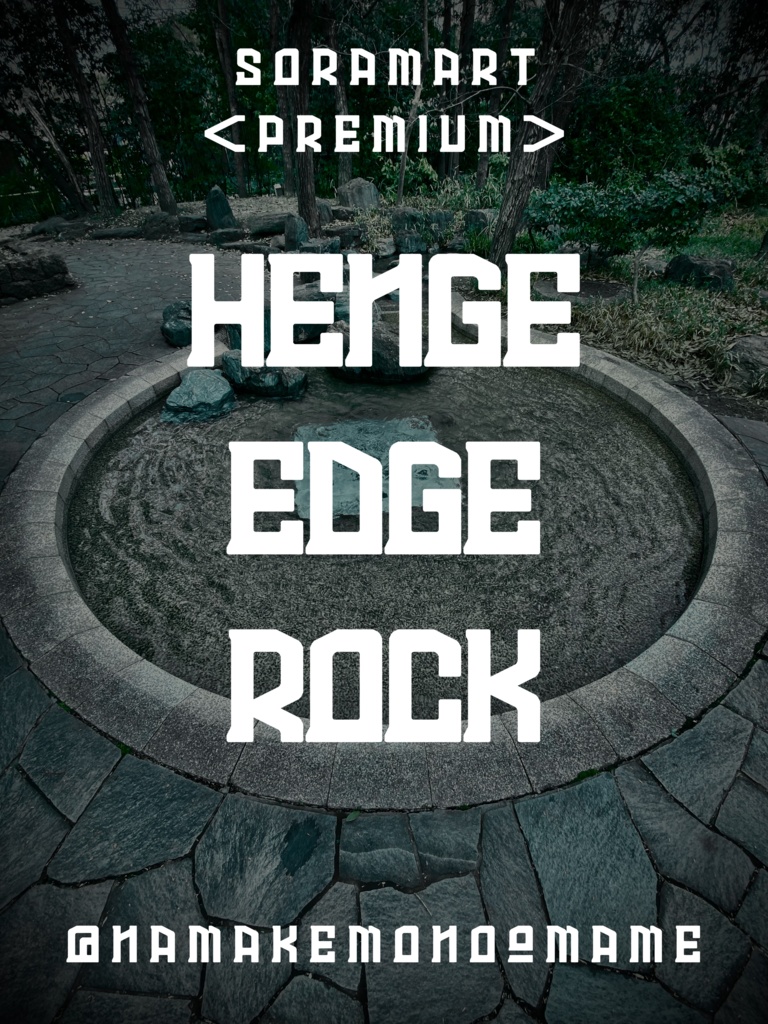
そらマートフォントデータ”Henge Edge Rock”Digital2,500 JPY카트에 담기기프트 보내기About Gift”ストーンヘンジ”をイメージした太字フォントにヒゲ飾りを加えた "Henge Edge Rock" です。 「TrueTypeフォントファイル」という形式です。 ダウンロードした後、Zipファイル内のデータをインストールしてお使いください。 このフォントは商用利用可となっております。 お客様の制作・創作活動のお役に立てれば幸いです。 ※使用上の注意事項などは、添付のReadmeをお読みください。 ※このフォントは有料販売専用商品です。そらマートVisit FANBOX!Fontsフォントデータ”Hazy Flap”そらマート0 JPYFontsフォントデータ”Amber Nouveau Tight”そらマート2,500 JPYFontsフォントデータ”Amber Nouveau Wide”そらマート2,500 JPYFontsフォントデータ”Amber Nouveau”そらマート2,500 JPYFontsフォントデータ”RANMMA Drive”そらマート2,500 JPYFontsフォントデータ”Dandy Laser Max”そらマート2,500 JPYFontsフォントデータ”Dandy Laser”そらマート2,500 JPYFontsフォントデータ”Bubblegum Beat”そらマート2,500 JPYFontsフォントデータ”Caltrop Serif LLL”そらマート2,500 JPYFontsフォントデータ”Caltrop Serif LL”そらマート2,500 JPYFontsフォントデータ”Caltrop Serif”そらマート2,500 JPYFontsフォントデータ”Tonik Crate Super Long”そらマート2,500 JPYFontsフォントデータ”Dot Eat Bug Acid”そらマート2,500 JPYFontsフォントデータ”Dot Eat Bug Mild”そらマート2,500 JPYFontsフォントデータ”Dot Eat Bug”そらマート2,500 JPYFontsフォントデータ”Solid Voltage Strike”そらマート2,500 JPYFontsフォントデータ”Solid Voltage”そらマート2,500 JPYFontsフォントデータ”Henge Edge Tall”そらマート0 JPYFontsフォントデータ”Henge Edge”そらマート0 JPYFontsフォントデータ”Chisel Stroke Wide”そらマート2,500 JPY더보기